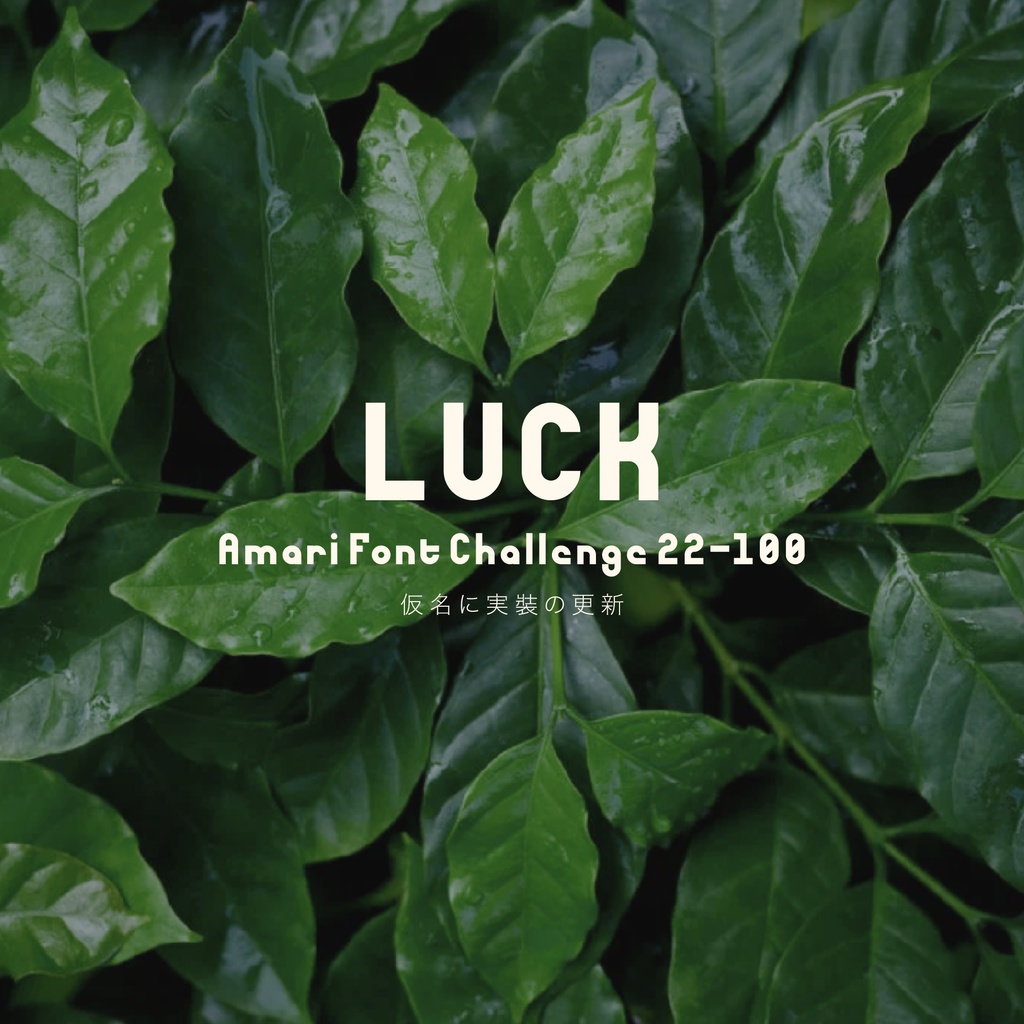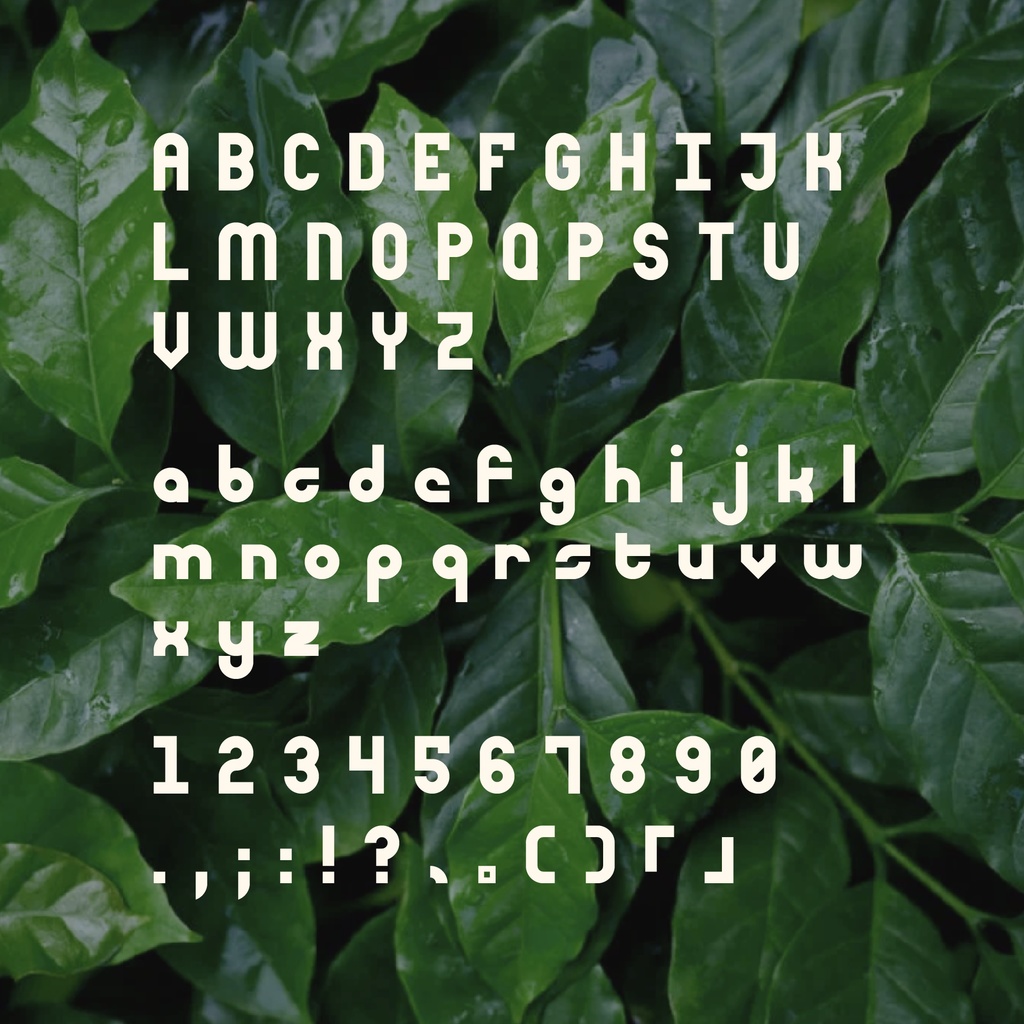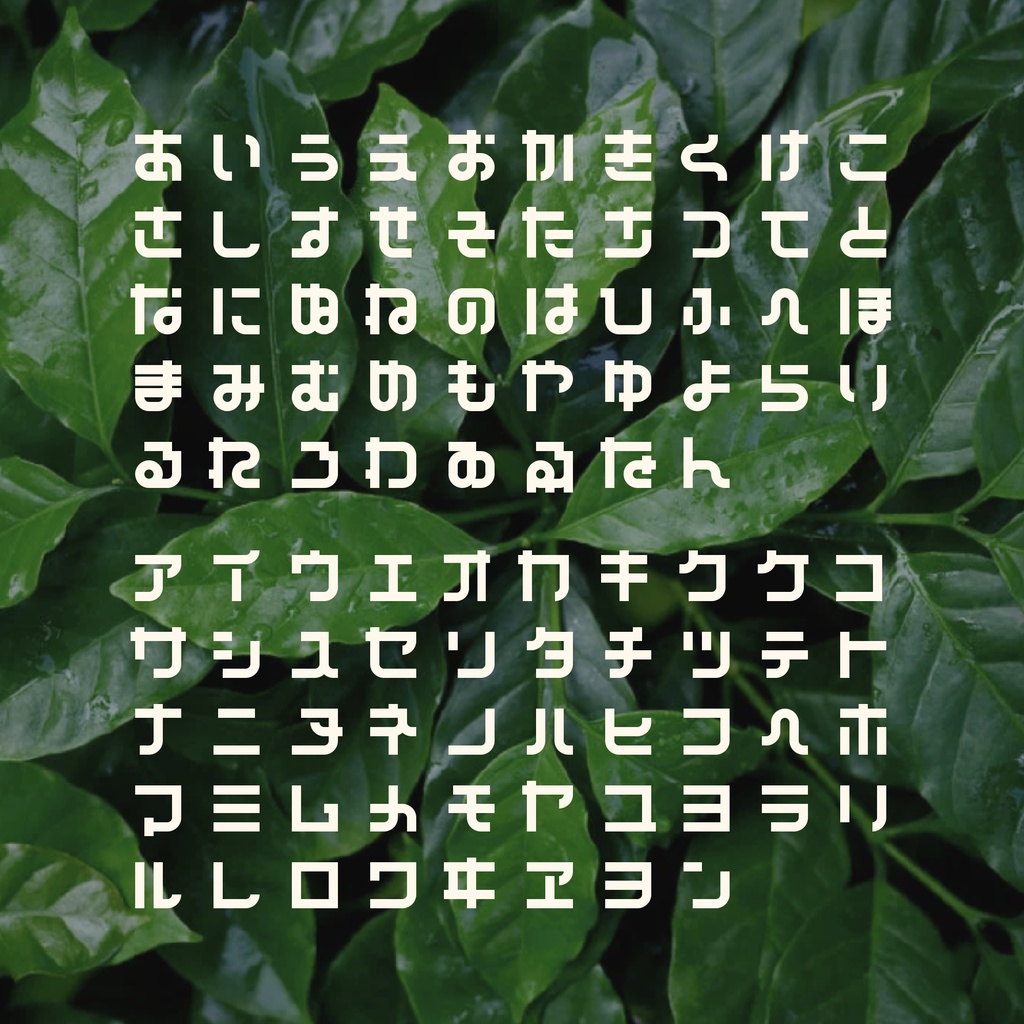
Amari Font Challenge 100-22 仮名実装 📢📢📢特記事項📢📢📢 100日フォントチャレンジ無事完了 この後、この100フォントに仮名を追加することに挑戦します。 英語よりも仮名の理解度が低いので、間違いがあれば遠慮なく教えてください、改善します! 有料にするか迷ったため、有料か無料かの選択肢を開放しています。 📢デザイン説明 文字の再現性を確保しつつ、画数の間隔に重視、視覚的なバランスを追求しました。 📢利用規約 個人、商用どちらでも利用可能です。 ✨✨✨もしもこのフォントが使用されたら、https://twitter.com/amari_designに教えていただけるとうれしいです!✨✨✨ 本素材を使用した作品については、リツイートなどの形で宣伝させていただく場合があります。 フォントのインストール等の技術的なサポートはいたしません。使用して発生したと思われる如何なる問題についても、作者は責任を負わないものとします。 著作権を放棄することはありません。 商標を登録したり、作者であると主張したり、データ自体を販売または再販したりすることは禁じられています。 このコンテンツの最終的な解釈権は作者に帰属します。 内容補充とバージョン更新は製作続けるです。使用する際は最新バージョンにご注意ください。 📢収録內容 ラテン文字、数字、仮名だけてを含む263グリフが含まれています。 ーーーーーーーーーーーー Twitter:https://twitter.com/amari_design Behance:https://www.behance.net/9f45706b ーーーーーーーーーーーー